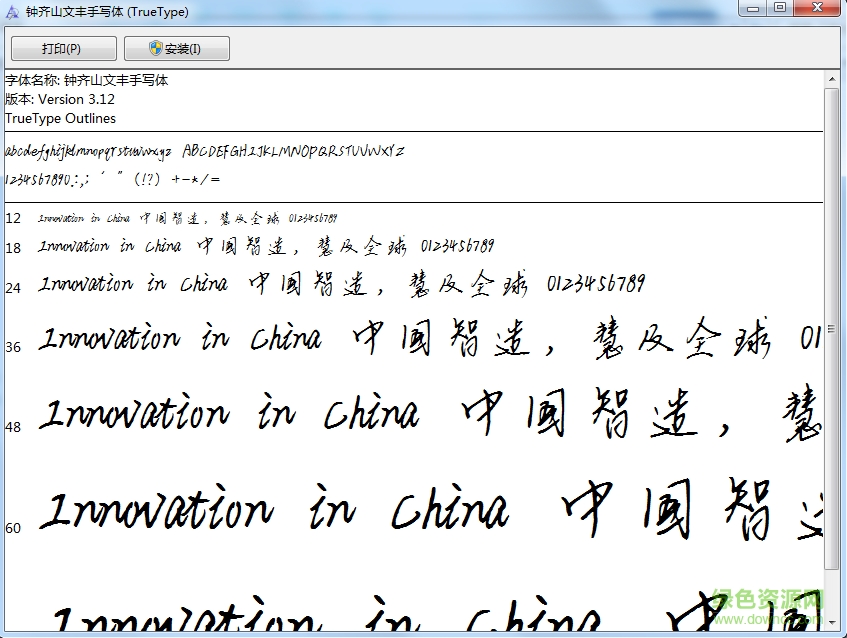
鐘齊山文豐手寫體是一款字跡清秀灑脫的手寫字體,無論是書寫中文漢字還是英文字母,都有著一股飄逸的美感,喜歡的朋友歡迎來綠色資源網(wǎng)免費(fèi)下載哦!
鐘齊山文豐手寫體是一款具有獨(dú)特手寫風(fēng)格的字體,它能夠?yàn)橛脩魩碇杏⑽碾p語字體,該字體形體端秀,給人感覺非常娟秀舒適!